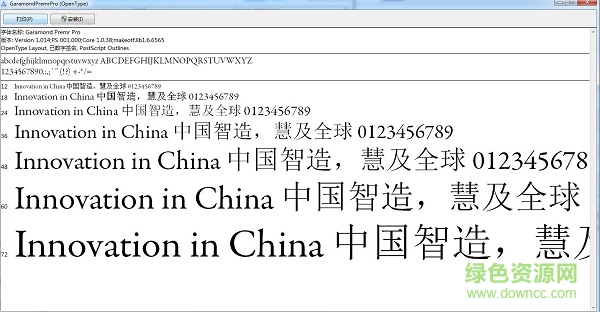
garamond premier pro字體是一款線條較細(xì)的襯線字體,結(jié)構(gòu)平穩(wěn),氣質(zhì)溫潤,細(xì)節(jié)表現(xiàn)豐富,給人的感覺簡約而不簡單,可用于網(wǎng)頁設(shè)計(jì)、印刷排版等領(lǐng)域,歡迎大家免費(fèi)下載!